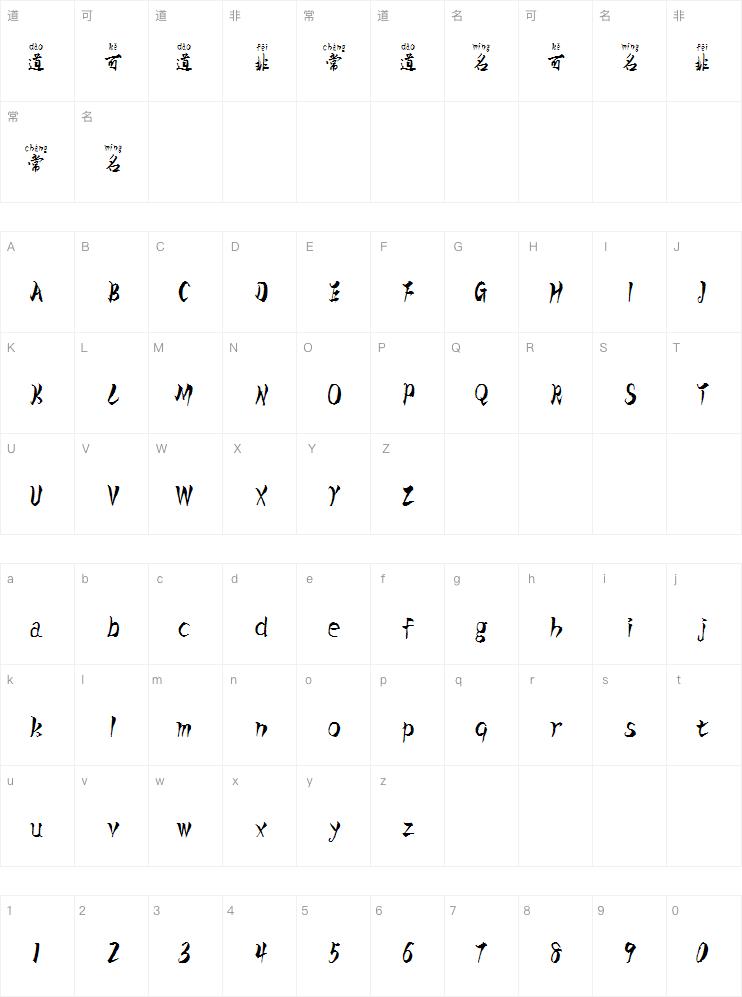
汉标高清唐寅大字行楷拼音
汉标高清唐寅大字行楷是一款根据明代书画家唐寅经典书法作品,经过再次调整制作的字库,唐寅字伯虎,后改字子畏,号六如居士、桃花庵主、鲁国唐生、逃禅仙吏等,明代画家、书法家、诗人。唐寅书法为画名所掩,主要学赵孟頫,更受李北海影响,笔画俊逸挺秀,婉转流畅,笔力稍弱,钩挑绵软,看不出一丝狂态。 汉标高清唐寅大字行楷是作者根据搜集到的真迹图片,运用抠图、处理背景图,运用造字软件经过再次调整,增减笔画轮廓及修复笔画缺失,调整书法文字比例结构,把每个文字调整到最佳使用效果,弘扬传承古代书法艺术经典,与现代技术相结合,实现完美设计应用。 字形用笔轻松,充分体现了笔锋之美。用笔饱满并且果断,体现出一种随性和灵秀。总字数6763个。 让更多书法爱好者能够通过电脑打字使用,真正感受到古代名家书法之美。 汉标高清唐寅大字行楷整套字体有如一气呵成,笔锋的立体感强烈,行笔迅捷华丽,其个性浪漫洒脱,适用于现代诗歌、短文的排版,以及文化、商业类品牌的广告语设计。